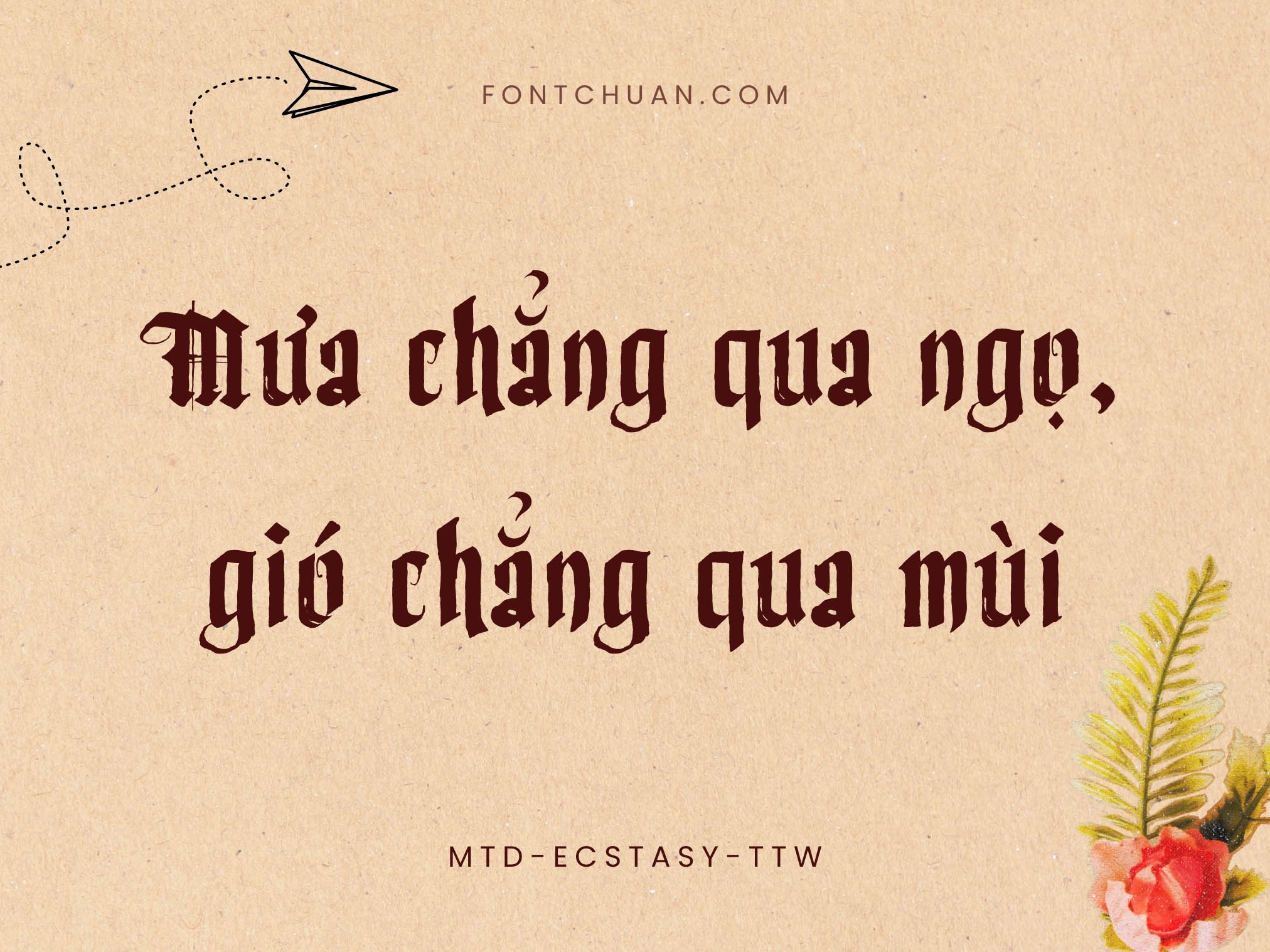
Font MTD Ecstasy Ttw Việt Hóa
Tác giả Font: Talavera
Font MTD Ecstasy TTW là một kiểu chữ viết tay độc đáo, được thiết kế bởi Talavera và đã được Việt hóa bởi Mộc Hạ. Font này hỗ trợ đầy đủ tiếng Việt cùng hơn 90 ngôn ngữ khác, mở rộng khả năng ứng dụng trong các thiết kế đa ngôn ngữ. Đây là một trong những phông chữ được cộng đồng thiết kế đánh giá cao và sử dụng trong nhiều dự án sáng tạo, đáp ứng nhu cầu đa dạng của người dùng.
MTD Ecstasy TTW nổi bật với các đường nét mềm mại và uyển chuyển, tạo cảm giác tự nhiên và nghệ thuật. Font rất phù hợp cho các thiết kế logo, tiêu đề, bao bì sản phẩm, thiệp mời và các ấn phẩm đòi hỏi sự tinh tế và độc đáo. Các ngành nghề phù hợp bao gồm quảng cáo, giáo dục, công nghệ, thiệp cưới và ảnh cưới. Font này cũng lý tưởng cho các sự kiện như Tết, Giáng sinh, Valentine và các lễ hội khác.